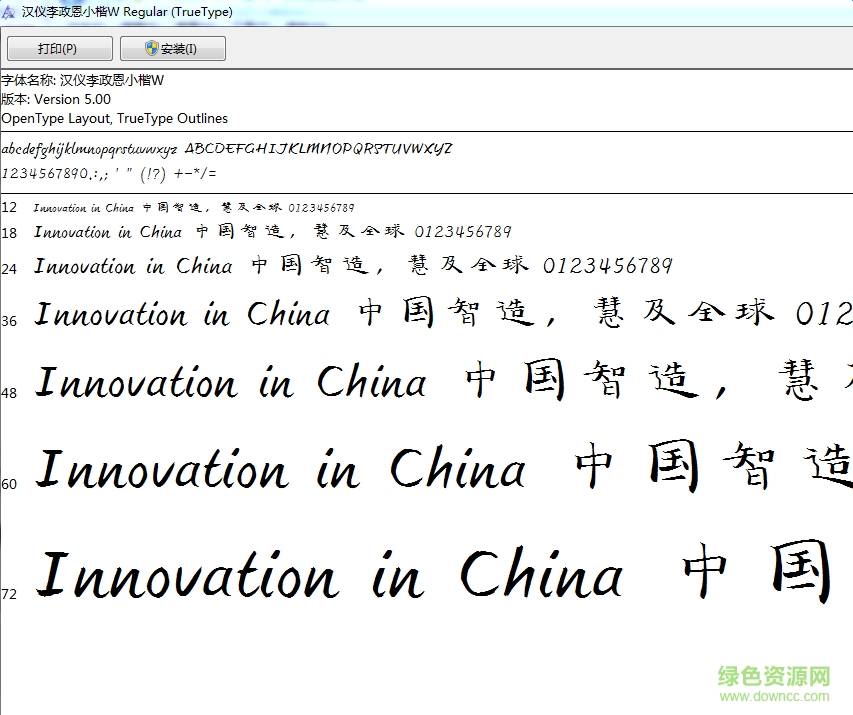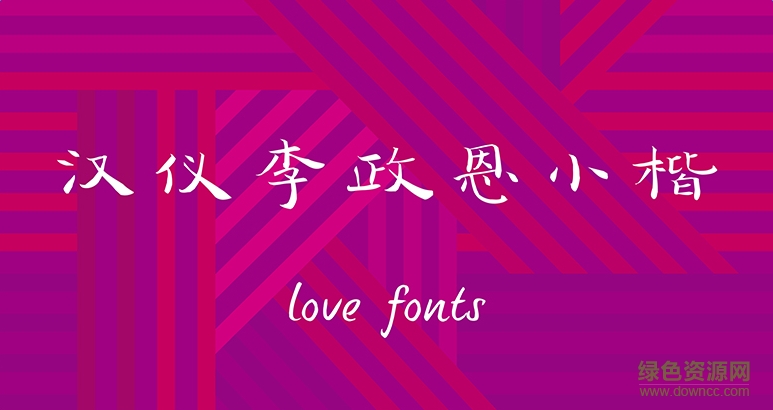
漢儀李政恩小楷字體是一款漢儀類優(yōu)雅楷體風(fēng)格字體軟件,李政恩小楷體筆畫工整,粗細不一,完美闡釋了楷體文雅特色,深受廣大書法家喜愛,還有更多好看字體歡迎來綠色資源網(wǎng)下載體驗!
漢儀李政恩小楷字體是一款應(yīng)用于藝術(shù)設(shè)計方面的簡體中文字體,該字體筆畫細膩,尾部的甩尾有力且有豐富的筆觸細節(jié),大字效果突出且引人注目;并且最大程度還原作者書寫字形,細節(jié)表現(xiàn)完整,且字庫完整,可以廣泛應(yīng)用于名片設(shè)計、新聞媒體、宣傳海報、ppt、影視制作以及內(nèi)容用字等領(lǐng)域。